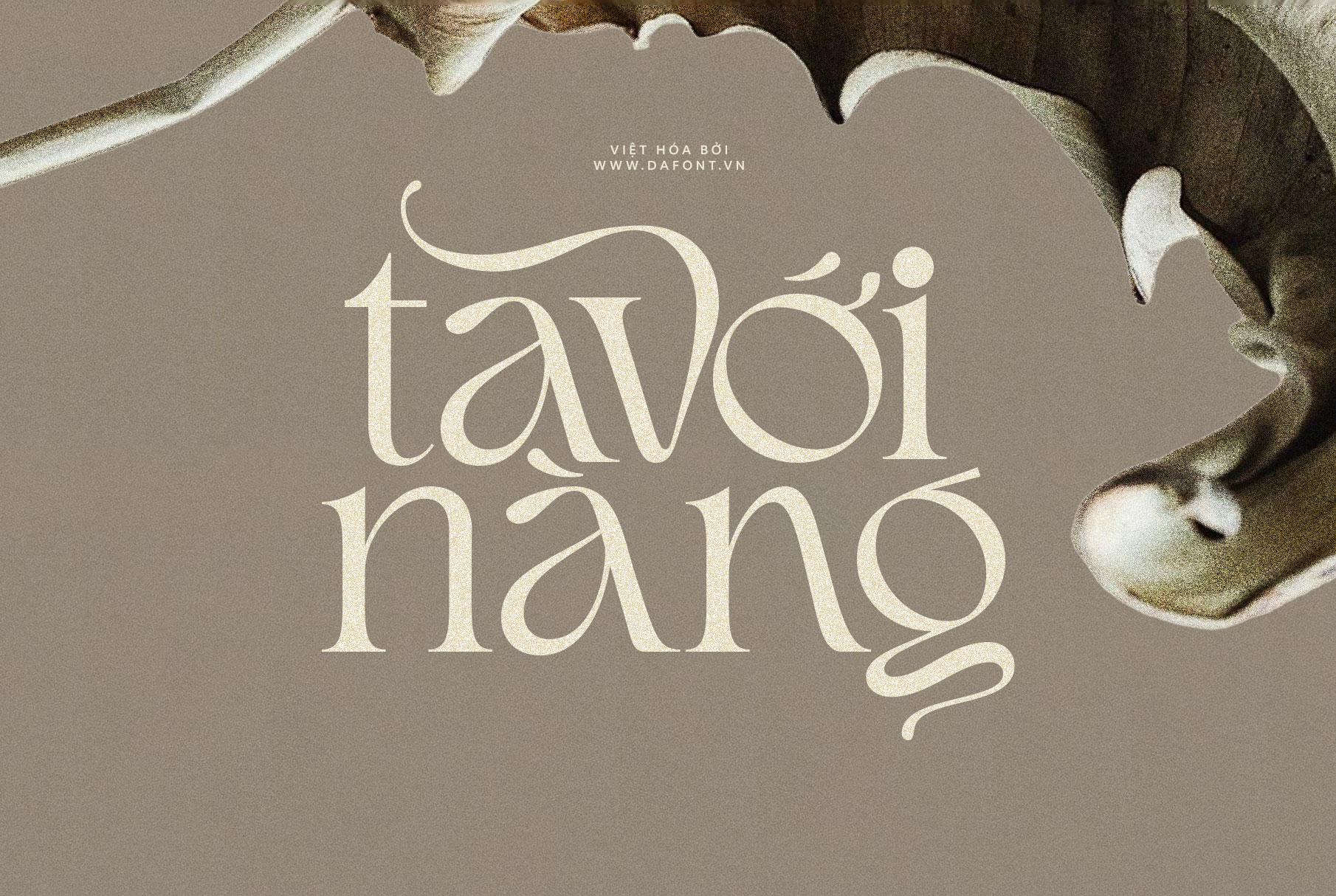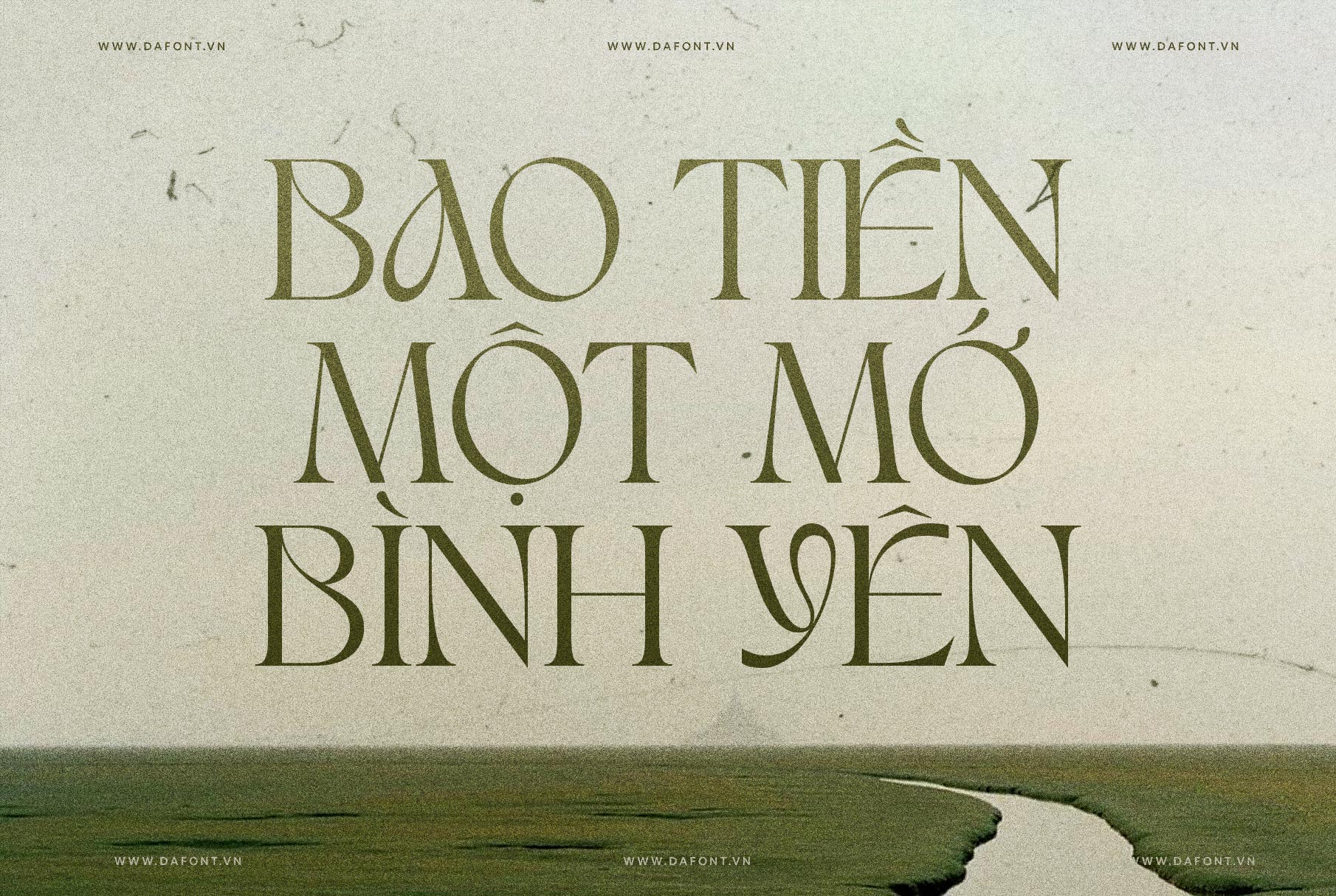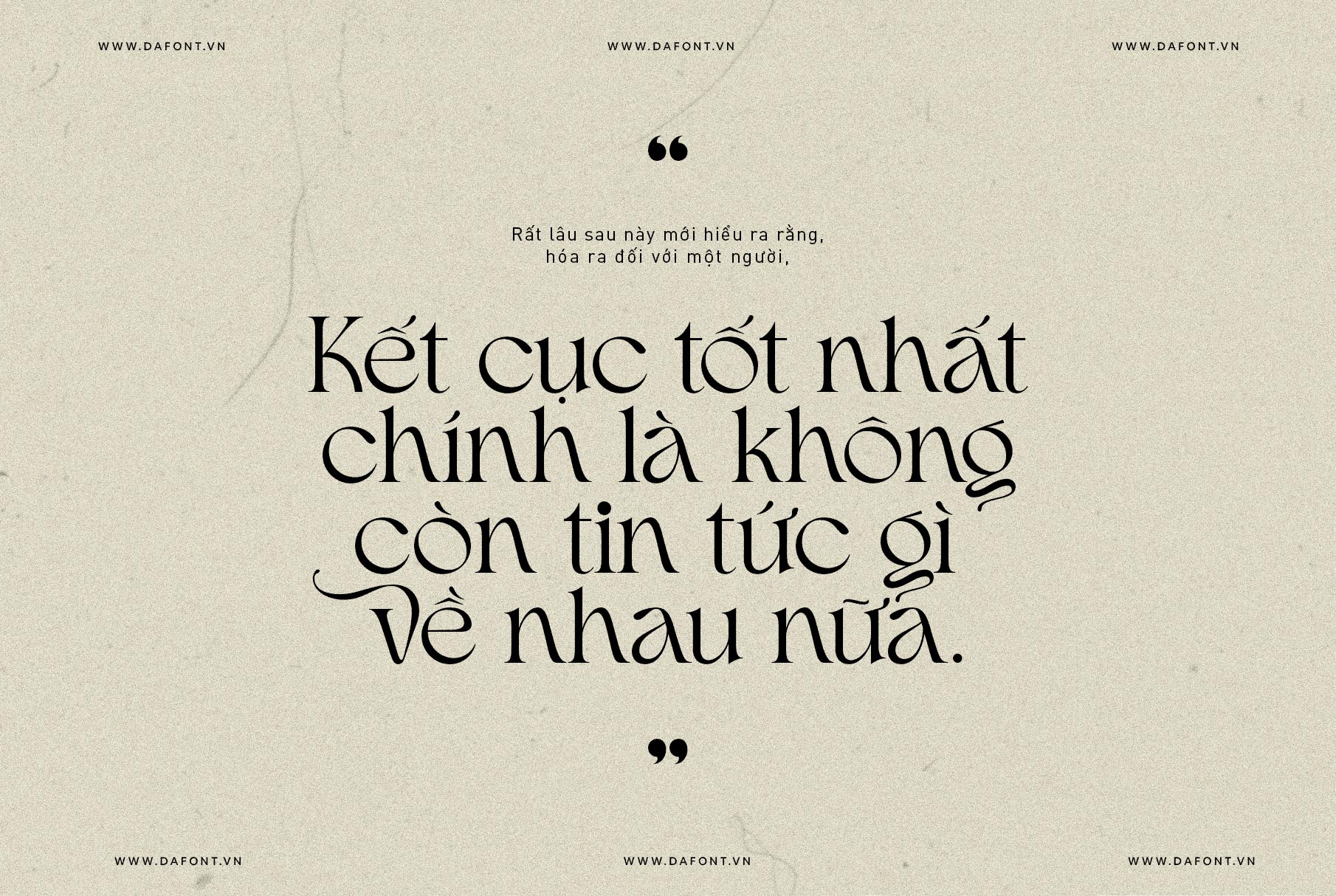
DFVN TAN – WAVERLY là một kiểu chữ serif đẹp mắt, ấn tượng nhờ vào sự thanh lịch, hiện đại và những nét độc đáo đầy quyến rũ. Nếu bạn đang tìm kiếm một font chữ để nâng tầm các dự án thiết kế của mình, TAN – WAVERLY chắc chắn sẽ là sự lựa chọn hoàn hảo.
Điểm nổi bật của DFVN TAN – WAVERLY
TAN – WAVERLY là một font serif tinh tế, được thiết kế với sự chú trọng đến từng chi tiết. Điểm nổi bật của font chữ này chính là:
- Sự thanh thoát: Các đường nét mềm mại và cân đối, mang lại cảm giác nhẹ nhàng nhưng không kém phần chuyên nghiệp.
- Chữ ghép độc đáo: TAN – WAVERLY đi kèm với hàng loạt ligature, giúp bạn tạo nên những kết hợp chữ sáng tạo, đầy phong cách.
- Nhiều glyphs thay thế: Các glyphs đa dạng mang đến sự linh hoạt, đáp ứng tốt mọi nhu cầu thiết kế từ logo, tiêu đề, poster đến các ấn phẩm in ấn cao cấp.
DFVN TAN – WAVERLY – Nét đẹp cổ điển và hiện đại
DFVN TAN – WAVERLY không chỉ là một kiểu chữ thông thường mà còn là công cụ thể hiện cá tính thương hiệu. Với sự kết hợp giữa nét đẹp cổ điển và hiện đại, phù hợp với nhiều lĩnh vực như: Thiết kế thời trang, mỹ phẩm, logo, bìa sách, thiệp mời, tạp chí và các ấn phẩm nghệ thuật.
Font chữ này có những “quirks” (điểm nhấn tinh tế) đặc biệt, giúp nó nổi bật hơn so với các kiểu chữ serif truyền thống, đồng thời mang lại nét quyến rũ khó cưỡng.
DFVN TAN – WAVERLY không chỉ là một công cụ thiết kế mà còn là biểu tượng của sự tinh tế và sáng tạo. Với những đặc điểm nổi bật và khả năng ứng dụng đa dạng, đây chắc chắn là font chữ bạn không nên bỏ qua.